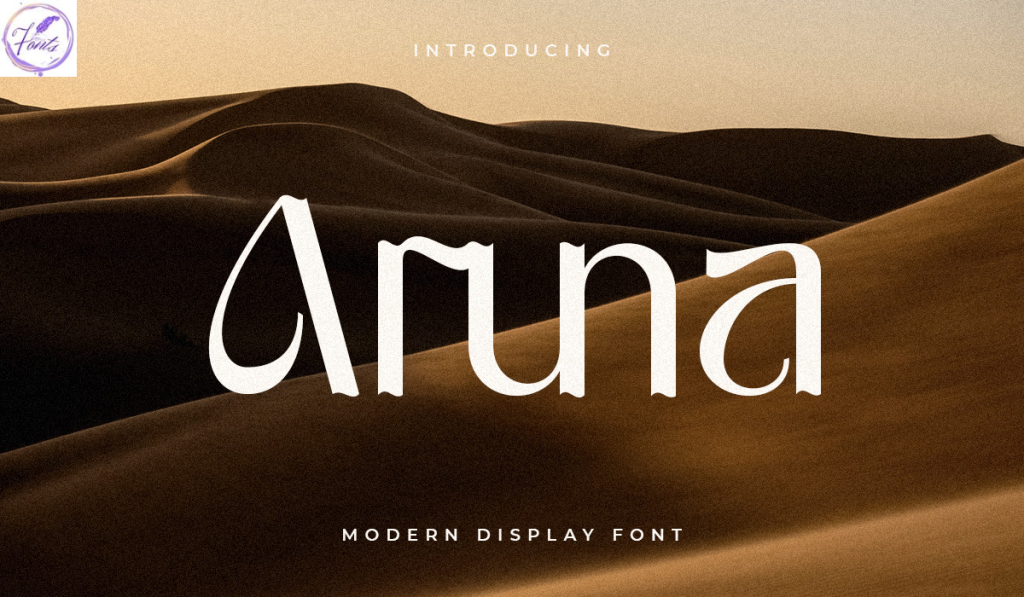
Font Aruna việt hóa
Tác giả: Yandidesigns
Bộ Font: Aruna
Phân loại: Cá tính, Độc đáo, Hiện đại
Kiểu chữ: sans-serif
Độ dày: Regular, Bold
Font Aruna là một phông chữ thanh lịch và hiện đại, được phát triển bởi nhà thiết kế Yandidesigns vào năm 2020. Với thiết kế mềm mại và thanh thoát, Aruna mang đến cảm giác tinh tế và chuyên nghiệp cho mọi dự án thiết kế. Phiên bản việt hóa của font này hỗ trợ đầy đủ các ký tự tiếng Việt, giúp người dùng tại Việt Nam có thể dễ dàng sử dụng trong các sản phẩm từ in ấn đến kỹ thuật số.
Đánh giá font aruna
Font Aruna đã nhận được rất nhiều đánh giá tích cực từ cộng đồng thiết kế. Các nhà thiết kế đánh giá cao sự rõ ràng và dễ đọc của font này, ngay cả ở kích thước nhỏ. Đặc biệt, sự linh hoạt của Aruna cho phép nó dễ dàng kết hợp với nhiều phong cách thiết kế khác nhau, từ hiện đại đến cổ điển. Ngoài ra, khả năng hỗ trợ đa ngôn ngữ, bao gồm cả tiếng Việt, làm tăng giá trị sử dụng của font này trong nhiều dự án đa dạng.